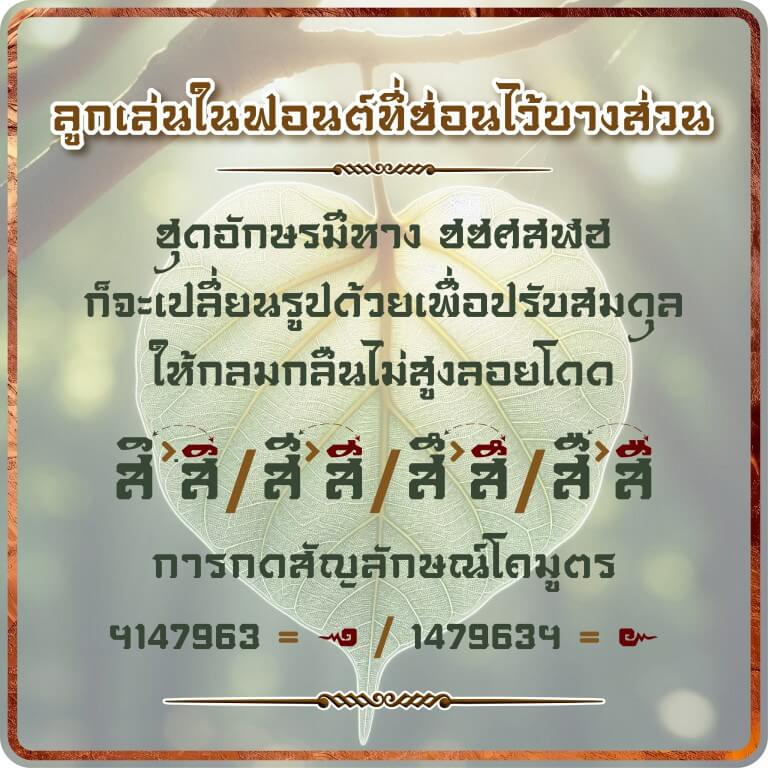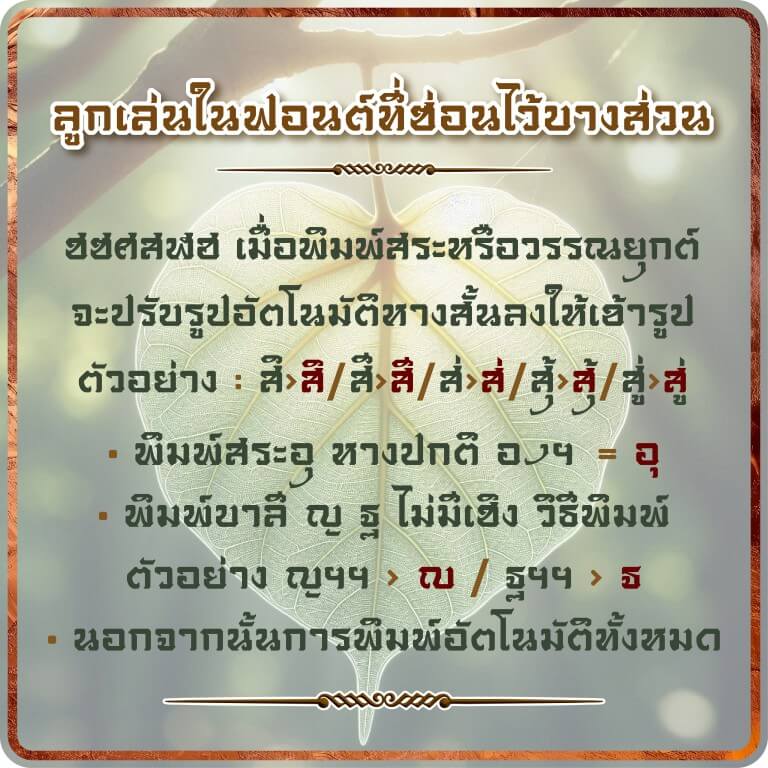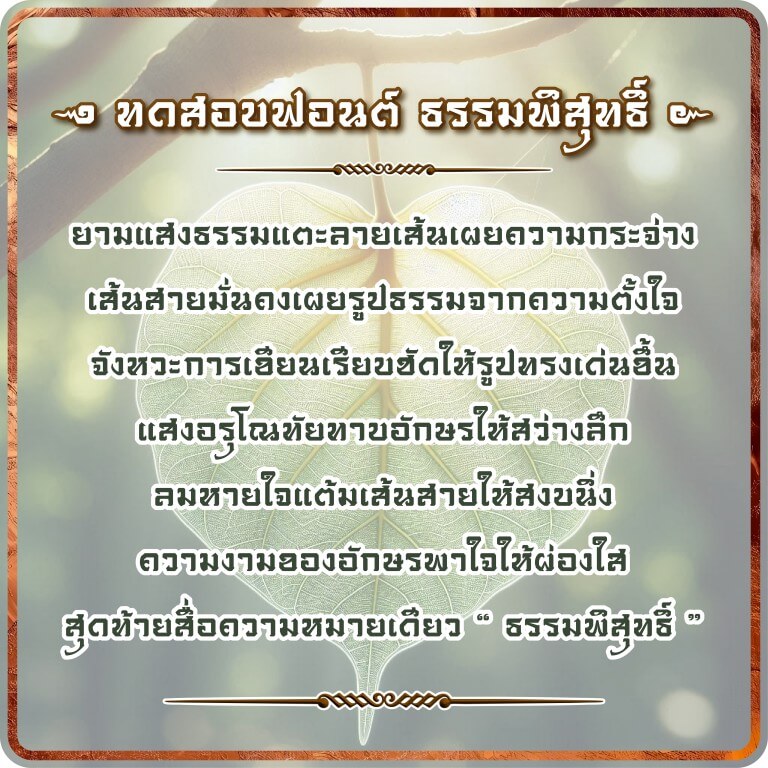
ธรรมพิสุทธิ์ (j.devilfont@Tham Phisut)
นำเสนอผลงานฟอนต์ชุดที่ 13 ธรรมพิสุทธิ์ ลักษณะฟอนต์ไทย พาดหัว หรือ งานป้าย งานไม้ งานcnc บทกลอน ป้ายร้านค้า สายมู ปกนวนิยาย นิตยสาร พระเครื่อง ของโบราณ โลโก้ สกรีนเสื้อ แสดงงานพิธี สายธรรมะ อักษรโบราณ สารคดี สื่อโฆษณา แบรนด์สินค้า ความเป็นเอกลักษณ์ไทยร่วมสมัย ฯลฯ
ลูกเล่นในฟอนต์ ธรรมพิสุทธิ์
ทดสอบรูปประโยคฟอนต์ธรรมพิสุทธิ์
รายละเอียด ฟอนต์ธรรมพิสุทธิ์
• ใช้งานด้วย kerning ปรับระยะห่างของชุดอักษรทั้งไทย-อังกฤษ
• ใช้ mark ในการจัด อักษร+สระ+วรรณยุกต์ เพิ่มการไล่ระดับสระ+วรรณยุกต์ อัตโนมัติ
• เพิ่มลูกเล่นที่ โ ใ ไ ที่ยืด-หด และเปลี่ยนรูปในเวลาพิมพ์อัตโนมัติ
• ตัวอักษรมีหาปรับหางสั้นเองเมื่อพิมพ์  สระอิ อี อึ อื  ่   ้   ๊  ๋  ์   ็  ั  ํ
• ชุด สระ วรรณยุกต์  ขยับเปลี่ยนไม่ให้ชนทับกับสระ วรรณยุกต์ ที่ตามหลัง
• เพิ่มวิธีการพิมพ์ โคมูตร ( ๛ ) กด  ฯ147963 ต้องการโคมูตรตัวพิเศษกลับด้าน 147963ฯ
• เพิ่มวิธีการพิมพ์ตัวบาลี ญ ฐ แบบไม่มีเชิง ด้วยการกด ญฯฯ  /  ฐฯฯ  จะได้ตัวที่ไม่มีเชิง
• ชุดอักษรนี้ไม่เน้นตัวอักษรอังกฤษ ตัวอักษรอังกฤษมีแต่ลักษณะตัวพิมพ์ใหญ่
• ปล. ยังมีลูกเล่นซ่อนอยู่อีก …ฯลฯ แต่ส่วนใหญ่จะเป็นการปรับอัตโนมัติแล้ว